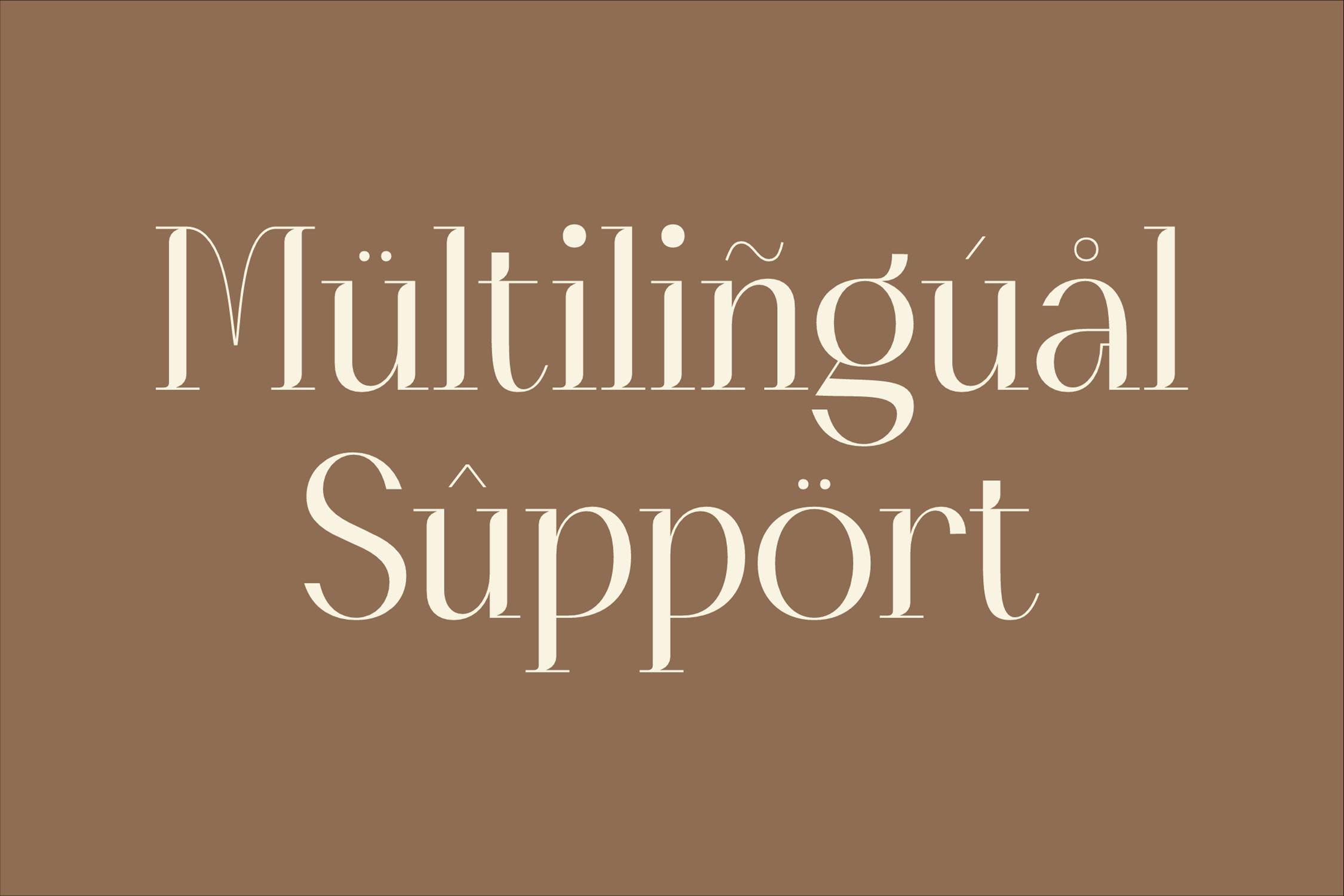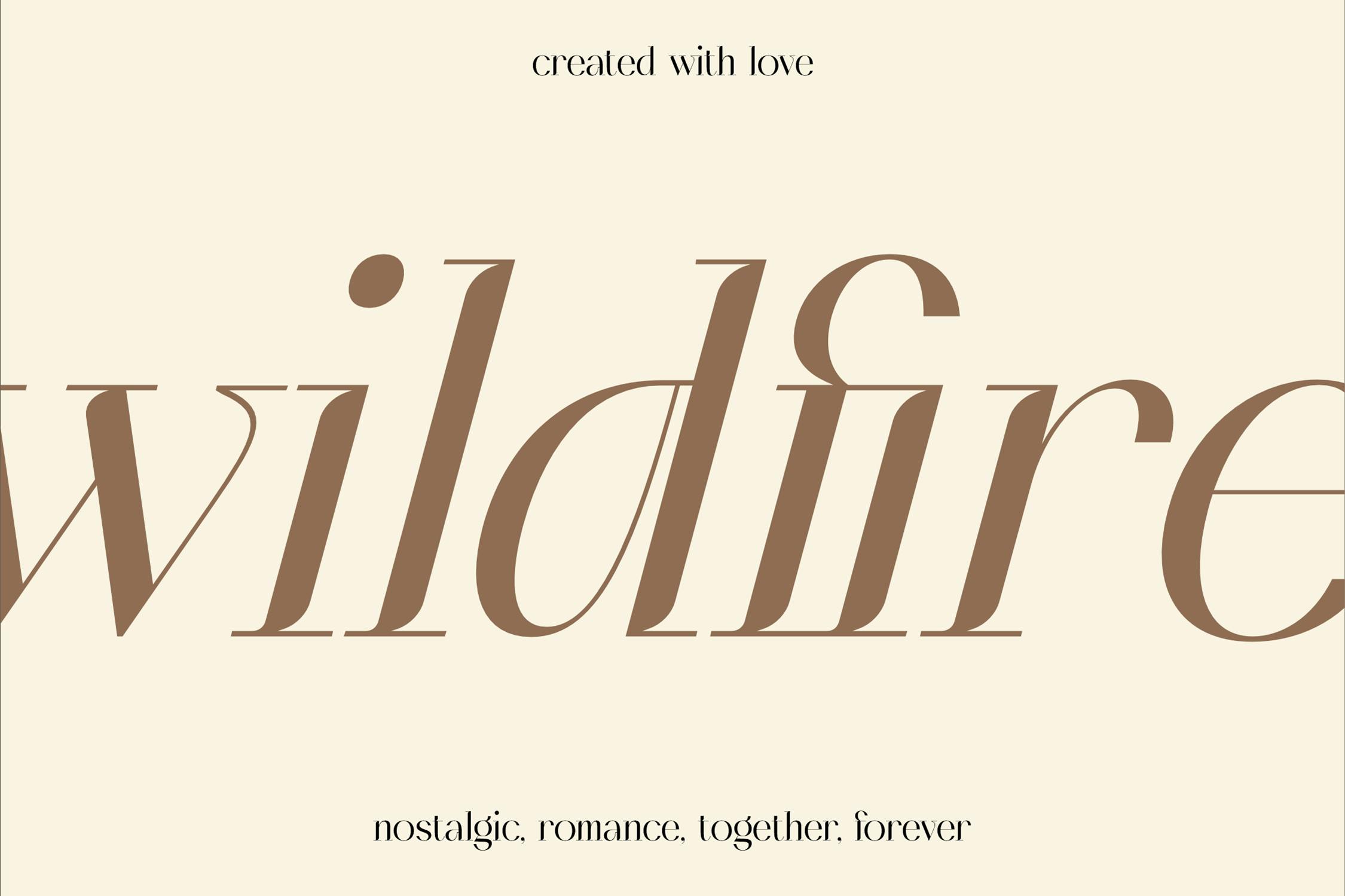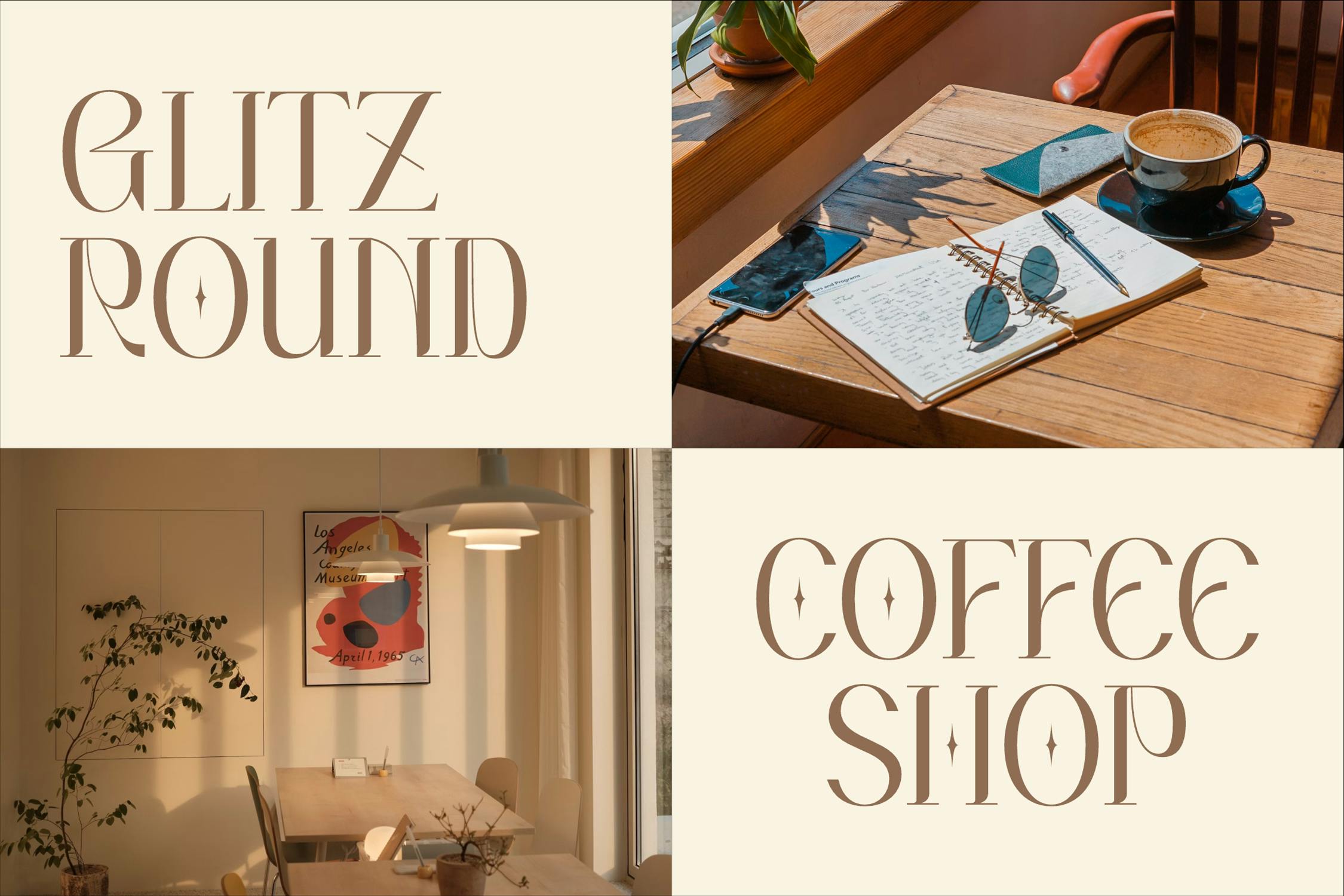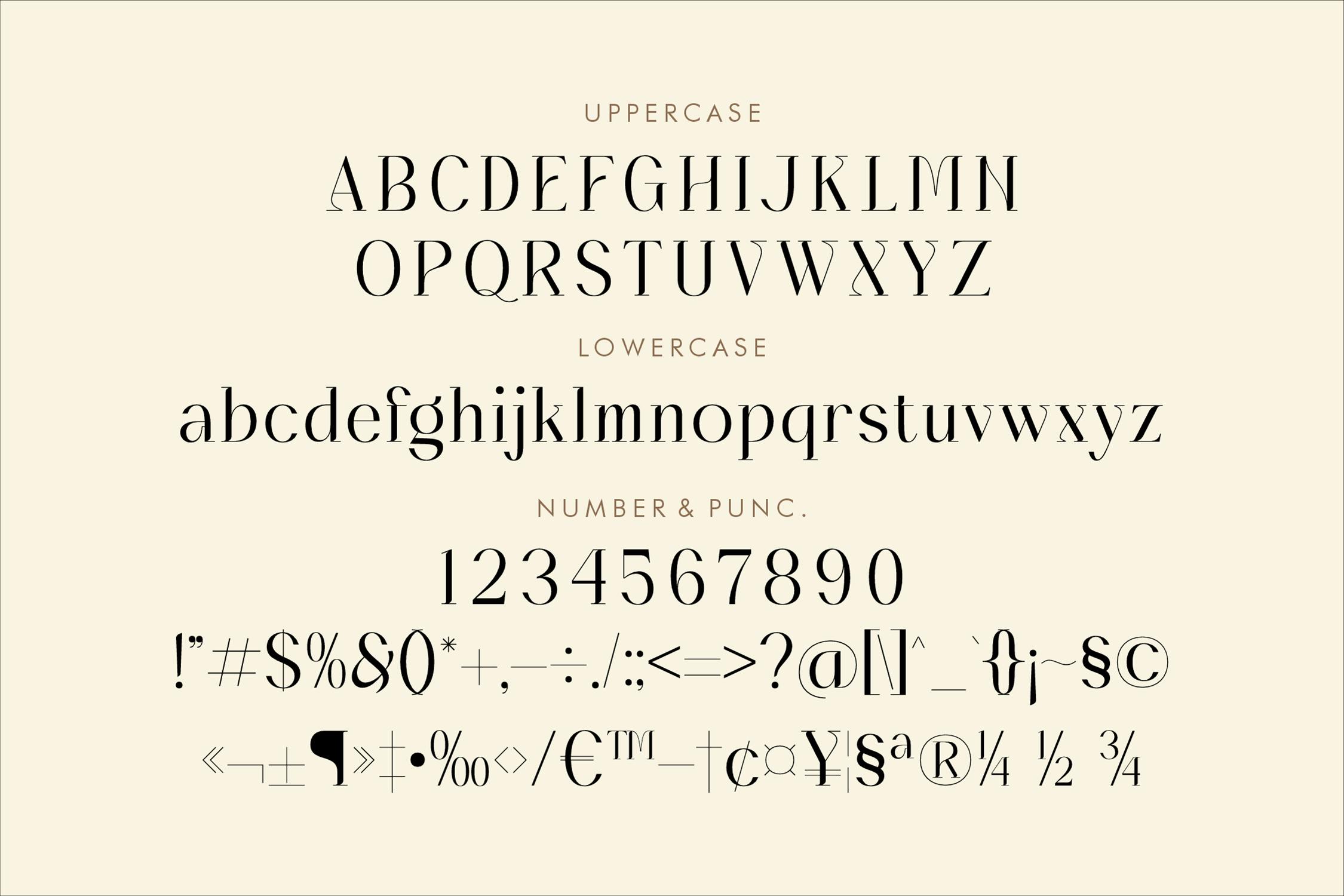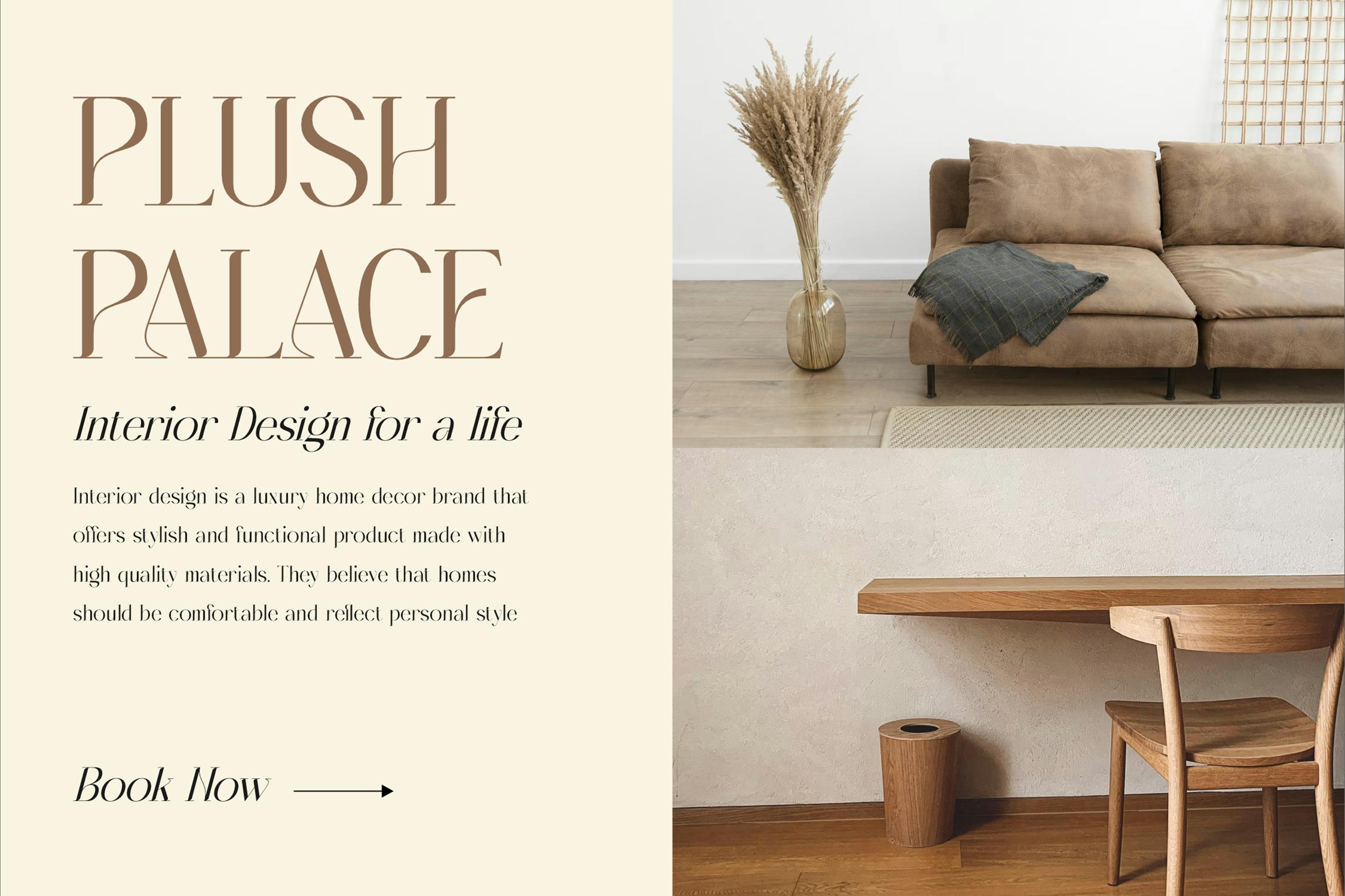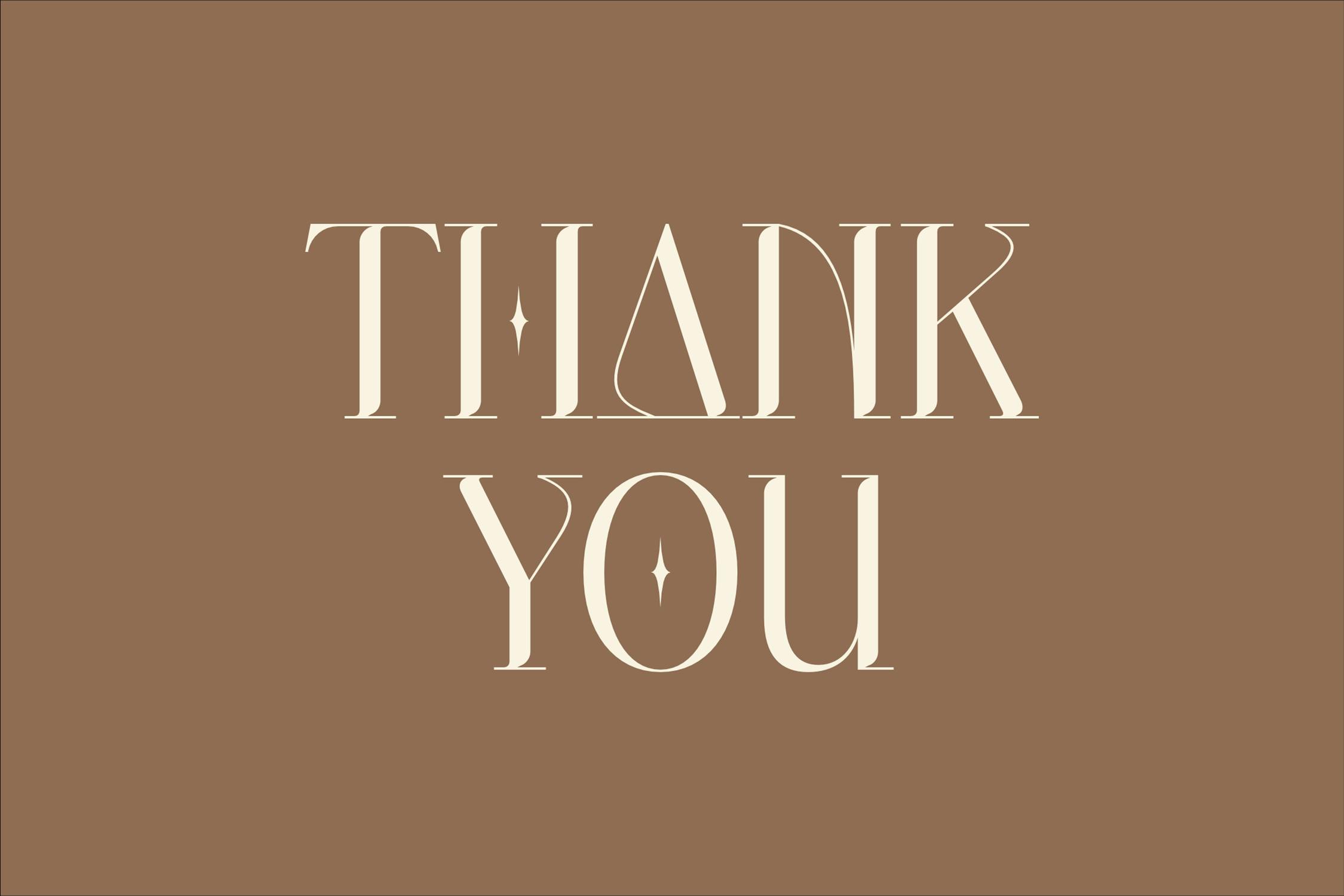
دانلود فونت بالورون: فونتی مدرن و جذاب
Balorune A Modern Type Face Font
فونت بالورون مناسب برای طراحی‌های دیجیتال و چاپی شما.
سلام خانم‌ها و آقایان، این یکی از فونت‌های ماست که به خوبی می‌تواند مکمل محصولات خلاقانه دیجیتال و چاپی شما باشد. این فونت برای طراحی پوسترها، پست‌های شبکه‌های اجتماعی، برندینگ و پروژه‌های شخصی بسیار مناسب است.